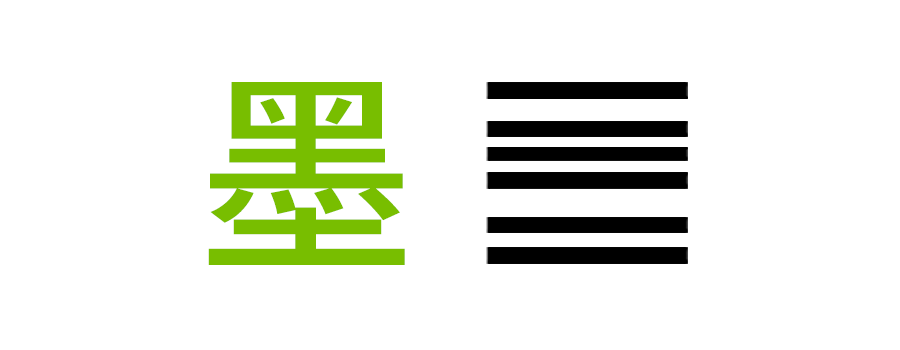
书法的主笔是指一个字中最主要的笔画,这个笔画对整个字起到画龙点睛的作用,让整个字主次分明,更加有精神和层次感。主笔的作用是破除字的均匀状态,避免字写得呆板。它一般位于字的右侧或下方,受到结体规律的影响。练习书法时,抓住主笔是关键,因为抓住了主笔,就抓住了这个字的重点。
而字体设计中的主笔则是汉字字体制作中较重要的笔画,而副笔为次要的笔画。
△ 绿色笔画为字体的主笔画
设计文字笔画时需要按主次关系依次安排粗细。主笔是视觉上较重要的笔画,设计上需要较粗;而副笔是相对次要的笔画,可以稍微减细。
△ 是否分别主副笔画所产生的字体对比
△ “墨”字主副笔画按照主副笔画原则按照顺序分配粗细的结果
如果在字体设计中不分主副笔画,可能会导致:字形可能会显得杂乱无章,缺乏和谐感。整体字形的易读性会降低,影响阅读体验。
因此,区分主副笔画是确保字体设计和谐、清晰和易读的重要步骤。